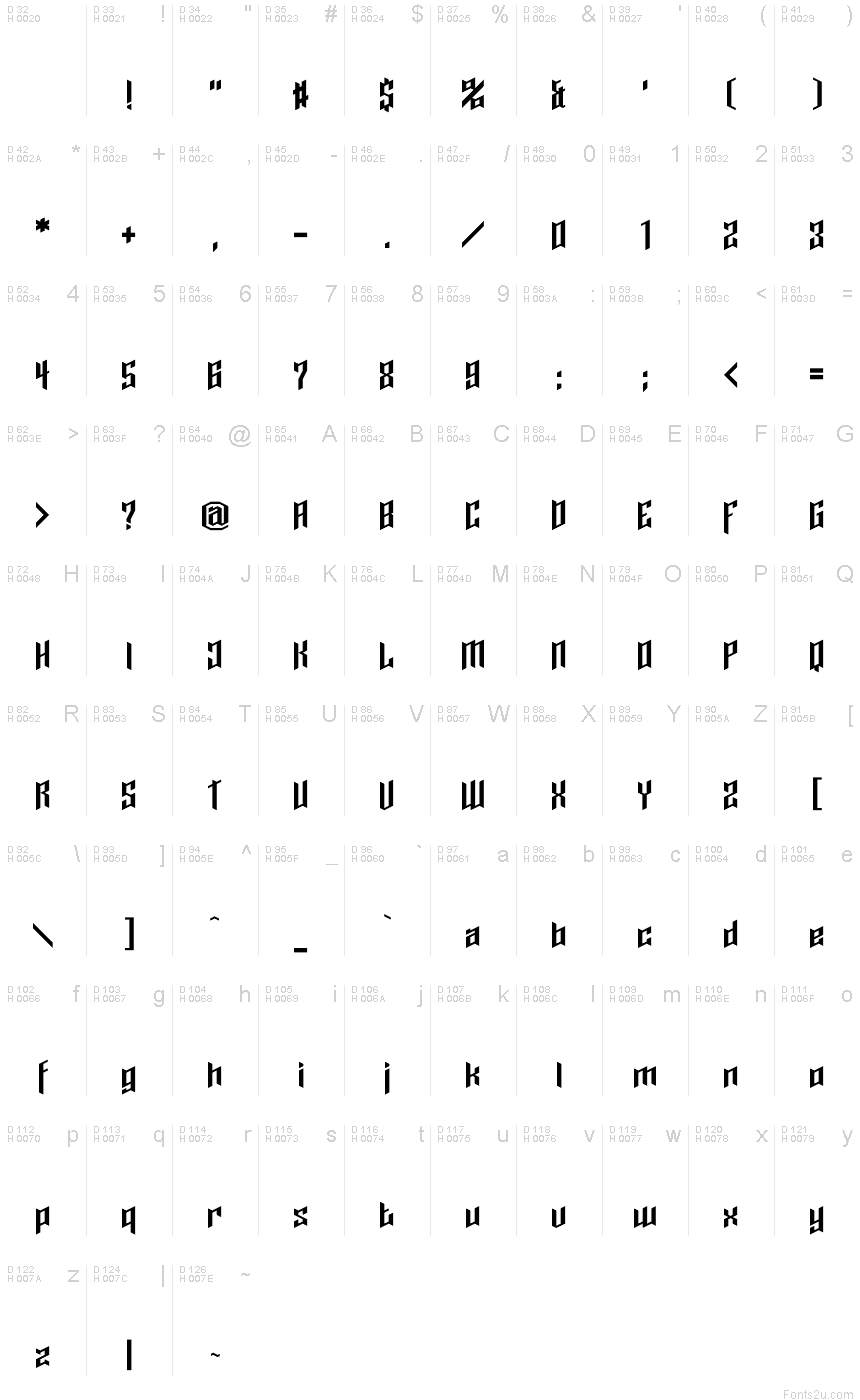
Cupra Regular от Тобиаса Зоммера (Tobias Sommer) — это бесплатный современный готический шрифт с острым характером в стиле блэклеттер (blackletter). Буквы опираются на резкие диагонали, скошенные углы и компактный вертикальный ритм, что придает шрифту свежий урбанистический вид, далекий от чисто исторических стилизаций.
Он отлично подходит для музыкальных плакатов, стритвир-брендинга, этикеток напитков, обложек изданий и заголовков, где требуется напряжение между средневековой эстетикой и современным стилем. Используйте его для коротких названий, монограмм или буквиц — острые соединения и плотный силуэт делают короткие слова графичными и выразительными.